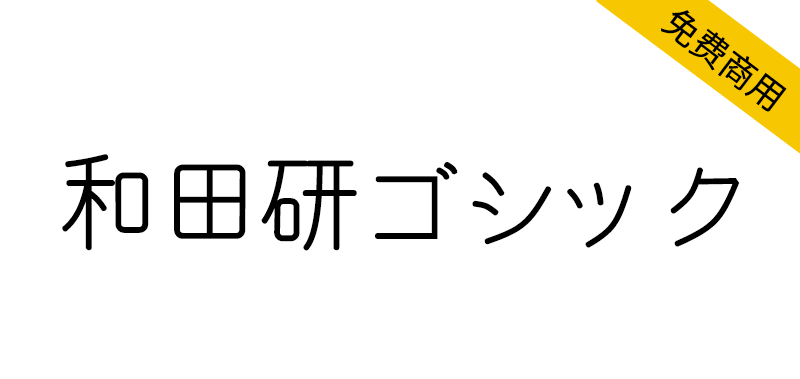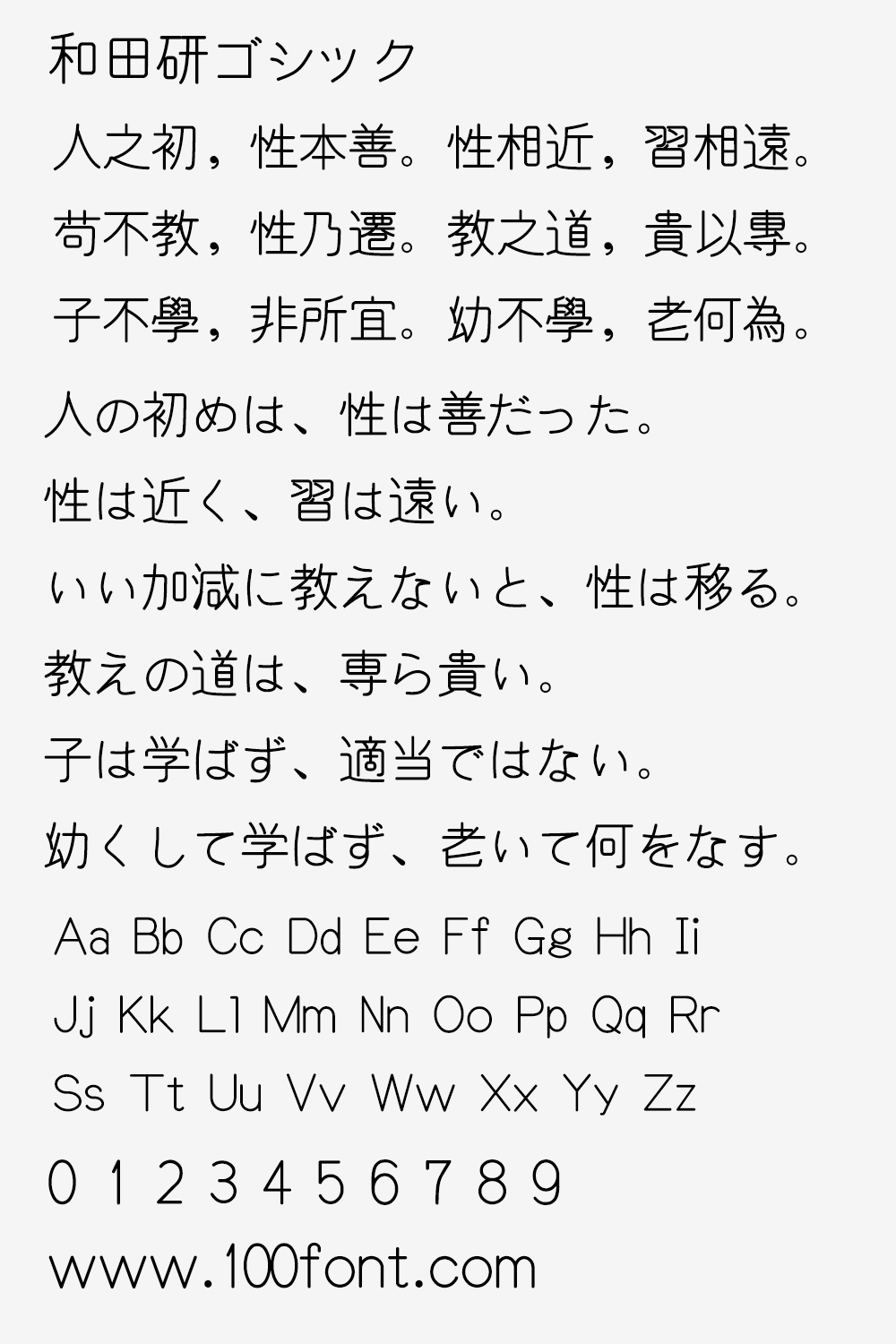
和田研ゴシック(和田研細丸ゴシック)是一款来之日本的细圆风格字体,作者是和田研,首次发布于2004年,虽然是一款比较老的字体,但作者目前还在更新维护,和田研以简单的元素来表达字体的美感,字体的直角转折处都以椭圆角来做替代,整个字体充满了浓浓的古典风格。(和田研细丸表示笔画较细,和田研中丸表示笔画较粗)